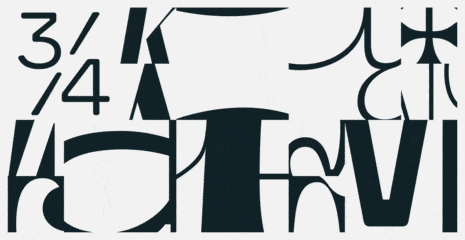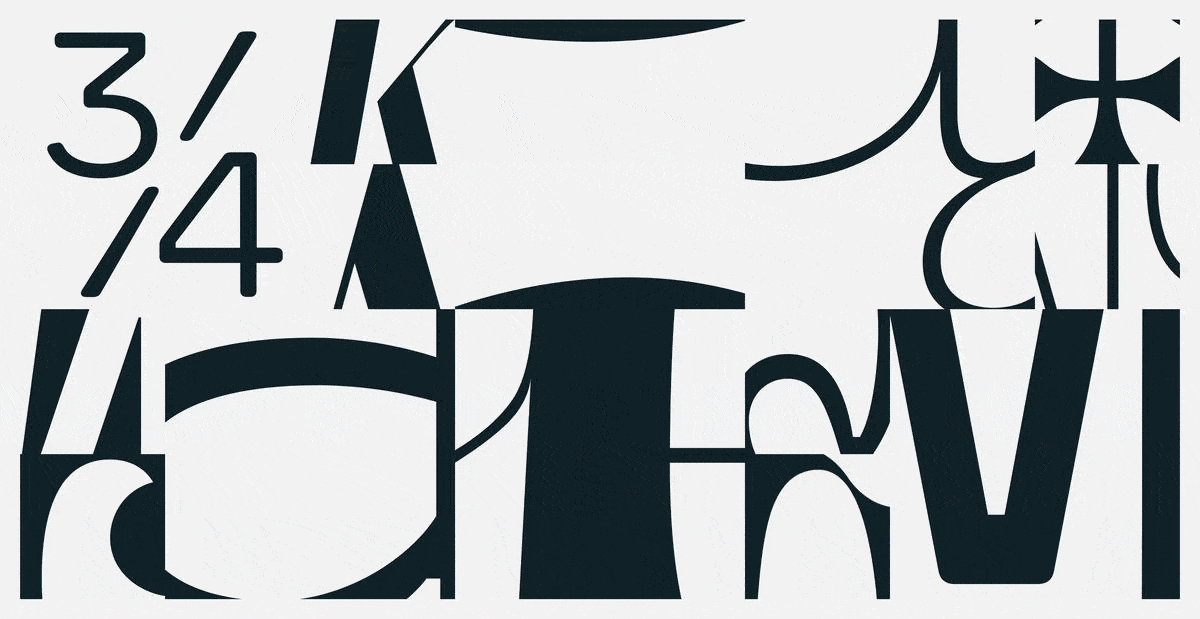
Show Me Fonts ist eine frisch gegründete Font Foundry mit Sitz in Berlin und startet mit einer sorgfältig ausgewählten Sammlung charaktervoller und vielseitiger Schriften. Die Schriften und der Schriftvertrieb sind eine Herzensangelegenheit von Gründer Bernd Volmer, der mit Show Me Fonts den nächsten Schritt geht und seinen langgehegten Traum Wirklichkeit werden zu lassen. Show Me Fonts entsteht nicht nur als Schriftvertrieb, sondern auch als dynamische Plattform, auf der er, Freunde und Kollegen ihre kreativen Energien bündeln, um Grafik Designern, Agenturen und Firmen mit frischen Schriften voller Charakter zu beliefern. Freut euch auf Premium-Display-Schriften für Branding, Poster und Packaging und sorgfältig gestalteten Textschriften für Fließtexte, Webseiten und Bücher.
Zum Start bietet Show Me Fonts eine vielfältige Auswahl von fünf unterschiedlichen Schriftfamilien, die verschiedenen Designanforderungen gerecht werden:
Capellini
Wie schaut eine Schrift aus, die von Mode inspiriert ist? Man assoziiert direkt eine Didone — eine klassizistische linear Antiqua mit hohem Kontrast und filigranen Serifen. Capellini geht einen Schritt weiter und bricht teilweise mit diesem Klischee. So ist Capellini deutlich lebhafter, zeigt humanistische Einflüsse und geht, was die Proportionen anbelangt, in die Extreme. Parallelen gibt es allerdings auch, wie beispielsweise der hohe Kontrast und die filigranen Serifen. Capellini ist variabel, sodass sich beliebige Kursivwinkel und eine Vielzahl an Breiten interpolieren lassen. Perfekt geeignet für Logos, Poster, Branding und Verpackungen.
Die Gestaltung von Capellini leitet sich von einer Logo-Skizze ab, die Bernd für Astrid Gleichmann, eine Berliner Videokünstlerin, gestaltet hat. Das Potential einer Skizze schien noch nicht ausgeschöpft und so überspitzte er das Design indem er eine extrem schmale Variante zeichnete. Aufgrund ihrer schmalen Proportionen und variablen Breite, ist Capellini ideal für Formate wie Instagram-Stories, Reels und Plakate.
Merkmale:
Filigrane Serifen, extrem schmal, kalligrafisch, schmale Proportionen
Das solltest du im Auge behalten: Capellini Numero1, bei dem die vertikalen Stämme den Anschein von aneinander gereiten Nudeln in einer Pasta-Box erwecken.
Chauncey
Eine zeitgenössische Neuinterpretation der Legibility Group Bleisatzschriften der 1930er Jahre. Chauncey bietet Display-Merkmale in der extrem dünnen Hairline und in dem extrem fetten Ultra Stilen sowie Textqualitäten von Light bis Bold, was sie vielseitig für Anwendungen in großen und kleinen Größen macht.
Chauncey ist das Ergebnis eines Revival-Projekts, das Teil von Bernds Type and Media Studiums in Den Haag im Jahr 2013 war. Oder besser gesagt: Chauncey ist ein Revival eines Revivals, da über die vergangenen Jahre so viel geändert und verbessert wurde an der Schrift. Als Hommage an Excelsior, eine Schriftart von 1931, hat Bernd eine Schrift gestaltet, wie sie von der Legibility Group im digitalen Zeitalter von 2023 gestaltet worden wäre. Was einst als ein einzelner Regular Stil begann, hat sich zu einer umfassenden Familie von 11 Stilen entwickelt. Chauncey ist ein echt europäisches Projekt, da es in Den Haag begann und in Berlin und Kopenhagen fertig gestellt wurde, mit der Hilfe von Linda Hintz. Linda spielte eine entscheidende Rolle bei dem letzten Schliff und den Details, bei Zurichtung und Kerning.
Merkmale:
Geringer Kontrast, abgerundete Kanten, ungekehlte Serifen
Das solltest du im Auge behalten: die filigrane Hairline für elegante Typografie und die krasse Ultra für prägnante Aussagen, die einen bleibenden Eindruck hinterlassen.
Petrosian Mono
Wie sieht eine Monospace Schrift aus, die nicht nur für Code-Editoren, ASCII-Art, Rechnungen und für die typografische Wiedergabe von Nukleinsäure- und Proteinfolgen taugt? Petrosian Mono ist eine vielfältige Schriftfamilie, die in kleinen wie in großen Größen performed. Sie zeichnet sich besonders in größeren Größen auf Postern durch ihre markanten Eigenheiten aus.
Bernd Volmer entdeckte in einer Antikbuchhandlung in Den Haag eine alte Schachzeitschrift. Die gesamte Zeitschrift wurde mit einer IBM Selectric-Schreibmaschine gesetzt. Am meisten fiel in der Zeitschrift die wunderschöne serifenlose Monospace-Schriftart Dual Gothic auf. Diese Schrift wurde in einem Text über den Verlust des Schachweltmeisters Tigran V. Petrosian verwendet. Die Schriftart, Petrosian Mono, leitete letztendlich ihren Namen von diesem Stück Schachgeschichte ab, und das Design der Zeitschrift diente als Inspiration für die Gestaltung der Schriftart.
Petrosian Mono begann als ein lockeres Revival, entwickelte sich jedoch zu einer eigenständigen Schriftart mit viel Charakter und Persönlichkeit. Die Hauptfeatures der Schrift sind übertriebene Inktraps und die abgerundeten äußeren Ecken, während die inneren Ecken scharfkantig blieben und dadurch ein spannender Kontrast zwischen scharfen und weichen Ecken entsteht. In größeren Schriftgrößen treten Merkmale wie große Inktraps in Buchstaben wie ‚M‘ in den Vordergrund und werden zu sichtbaren Charakterzeichen.
Merkmale:
Monospace-Sans-Serif, abgerundete Außenkanten, scharfe Innenkanten, große Inktraps
Das solltest du im Auge behalten: eine proportionale Version von Petrosian, die in Zukunft veröffentlicht wird.
Seraphs
Eine variable Schriftfamilie, die zwischen verschiedenen Serifenstilen interpoliert. Seraphs dient als ideales Prototyping-Werkzeug für Grafikdesigner, um verschiedene Designrichtungen zu erkunden und mit einer Schriftart zu experimentieren. Es kann zwischen 6 verschiedenen Serifenstilen und verschiedenen Gewichten interpoliert werden.
Merkmale:
Ideal für Display Größen, riesige x-Höhe, ausdrucksstark, asymmetrischer Kontrast, konvexe Strichenden
Das solltest du im Auge behalten: die unkonventionellen „t“ „A“ „M“ „V“ und „W“